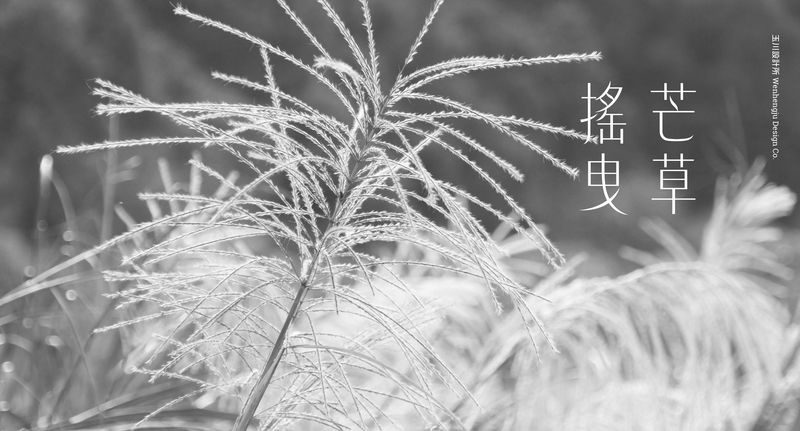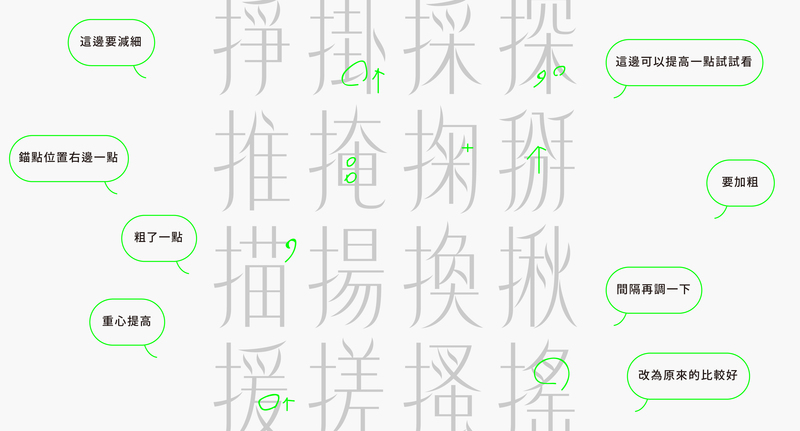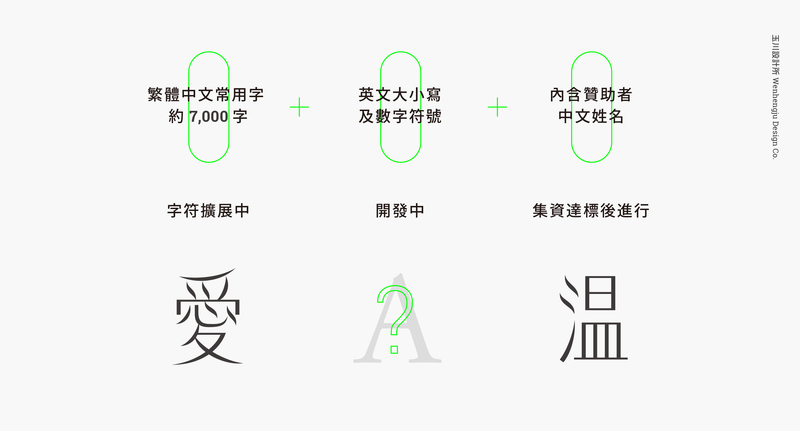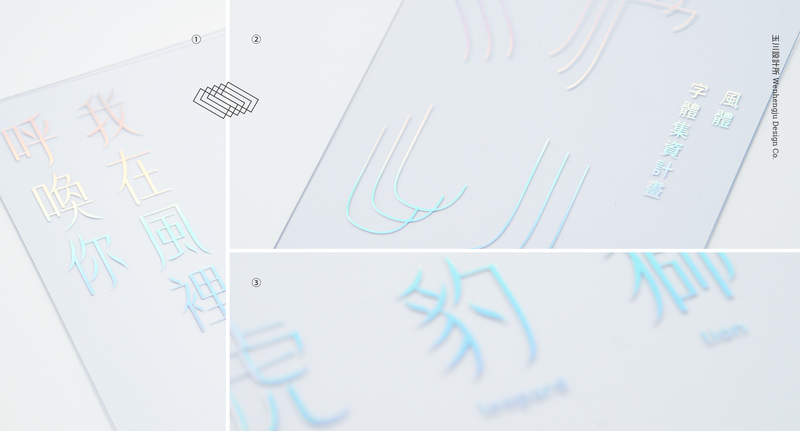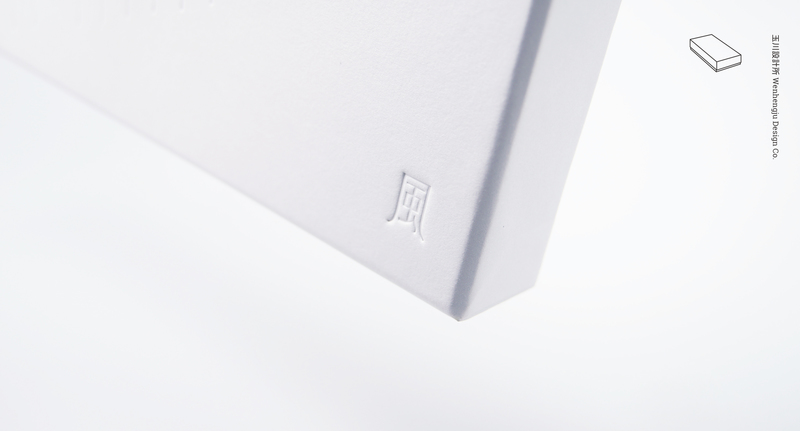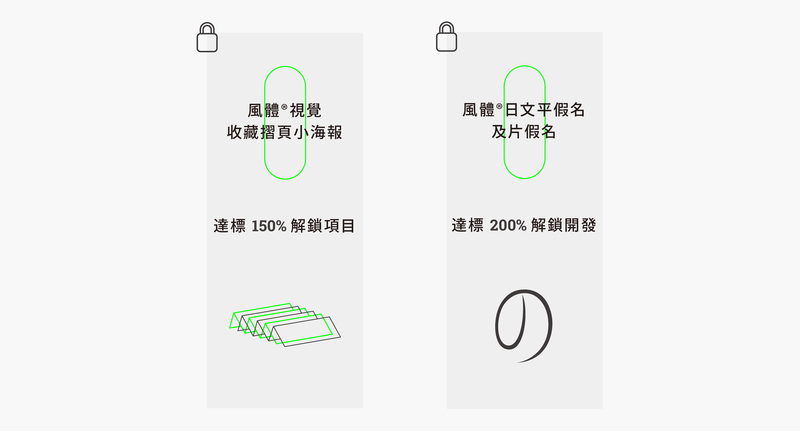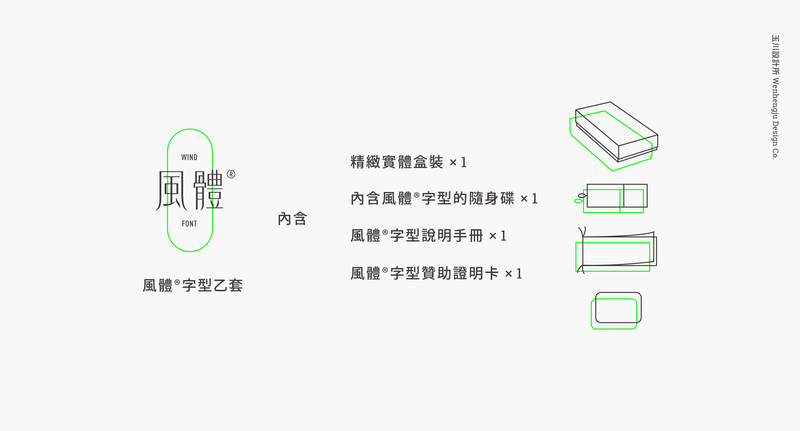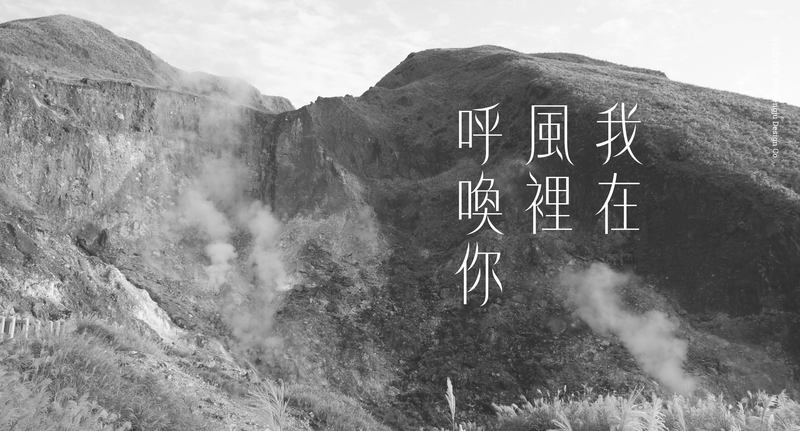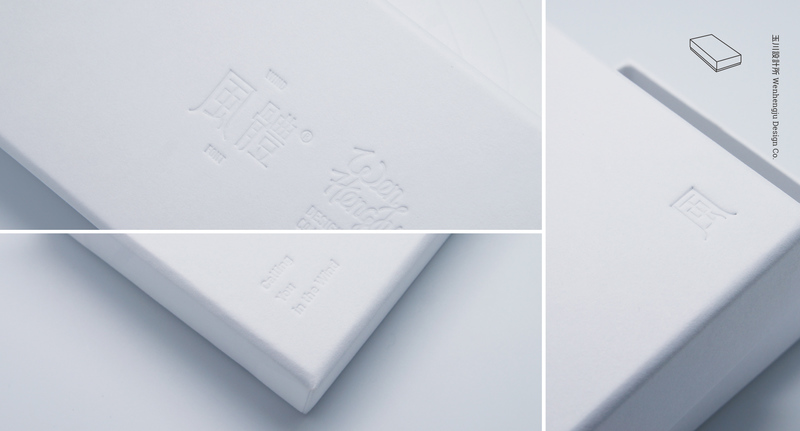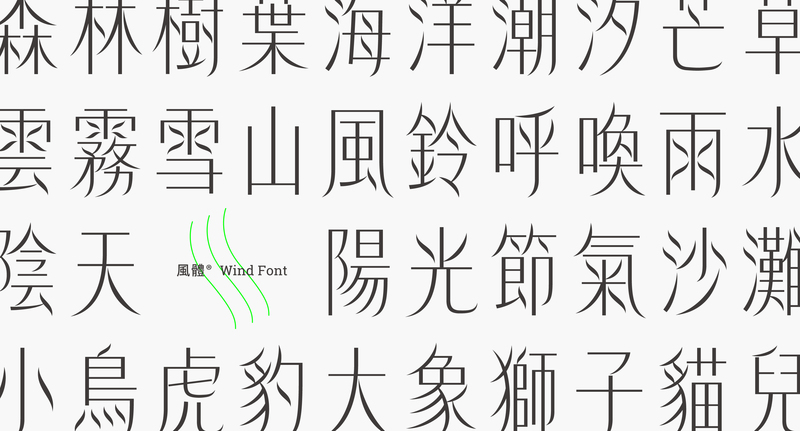
我在風裡呼喚你 — 風體 Wind Font 字型集資計畫
風體®是一套獨立設計的標題類繁體中文字型,需要透過這次的集資計畫,和支持喜愛風體® 的你一起協助完成這套字型,讓臺灣字型越來越豐富多元,也有更多美麗的風景。
風體®是一套由設計師獨立設計的創意繁體中文字型,起因於要做一個與「空氣」聯想的作品,就這麼在不經意的時候形成了。
適用於標題類字型的風體,字身瘦長顯得優雅氣質,並以自然間的事物作為基礎:風、飄落的樹葉、茶葉、搖曳的芒草,繪出具有這些特色的筆畫後,逐漸形成一個又一個的繁體中文字符。
風體,一套創意的繁體中文字型:悄悄地乘著風,為字型拂來新的氣象。
▲ 用風體的筆畫,描寫在風裡搖曳的芒草。
▲ 「點」,是風體最大的特色。
初期以手繪將字的骨架及筆畫風格決定好後,進入造字軟體拉出風格一致的部件和基本字,經過反覆修正後,慢慢延伸形成一個個的字符,最後就可輸出成我們鍵盤敲得出來的數位字型。
▲ 從初期手繪的開發階段、製作涵蓋大部分的部件以確立整體風格,一直到最後延伸出大量的字符,過程可耗時數年。
▲ 風體在標題字的表現上優雅且有空氣流動感。
▲ 不論是詩經、古詩還是現代詩,風體皆詮釋出一番文人風情。
風體是獨立設計創作的,光是完成整套標題類的常用七千繁體中文字其實相當不容易,需要經過長時間的反覆修改與調整才能一點一點接近理想中的樣子,是一項艱鉅的挑戰。
什麼是獨立設計字型?#
由設計師製作字體,沒有經由字型公司或相關管道,自行發行的字型。你也可以解釋為類似獨立出版的概念。
▲ 上上下下,左左右右,加粗減細,這就是設計師日常的內心OS。
▲ 事實上,在這八個版本之後,「愛」的版本還在不斷新增,務必要做出最符合風體風格的樣子。
風體預計完成繁體中文常用的七千字:以教育部公布的常用字為主並繼續延伸;並設計開發風體專屬的英數符號。當然,贊助風體的朋友們別擔心,你們的中文姓名無論有沒有罕見字,都會在集資達標後第一優先製作成風體,以回饋喜愛這套字型的朋友們。
▲ 風體適合表現標題字,常用七千字已能涵蓋大部分標題的使用,並設計符合風體的英數符號。
風體,不只是字型,更是一件值得收藏的藝術作品。#
想讓字型不只是字型而已,這是風體想要傳達的最重要的一件事。字型是一件設計作品,但字型不只是具有實用性,它也可以有美的收藏價值。
當你看著風體,可以感受到它的溫柔、它的溫度、它的生命力;透過各種材質和形式,表現和襯托出字體的靈魂,字型也就被賦予了嶄新的面貌。